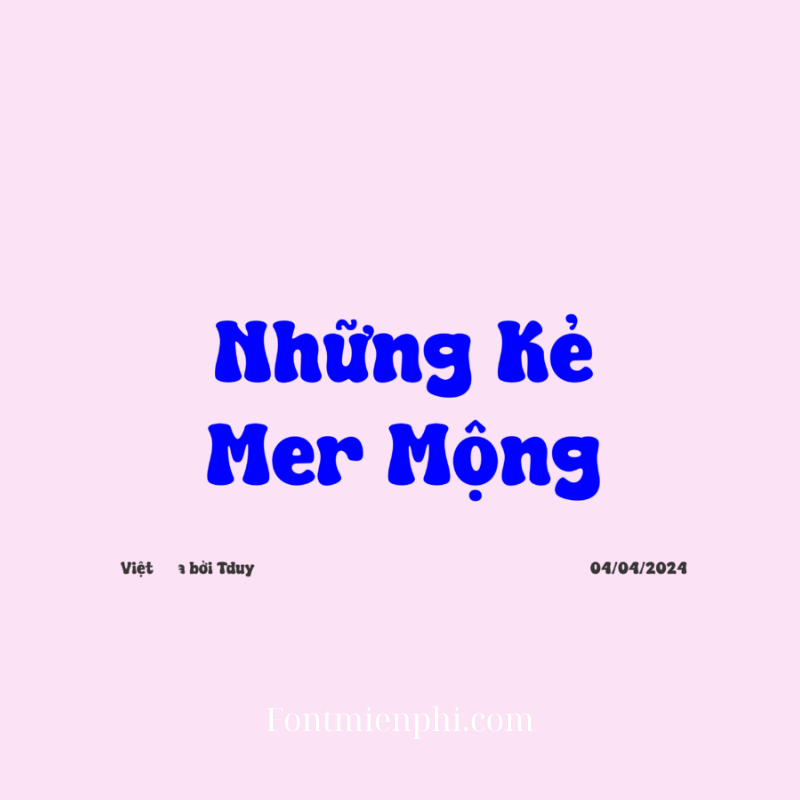
Việt hóa font DL Super Dream
Việt Hóa Font DL Super Dream – Phông Chữ Đẹp, Sáng Tạo Cho Thiết Kế
Giới thiệu
Font DL Super Dream là phông chữ nghệ thuật được ưa chuộng nhờ nét chữ mềm mại, thanh thoát. Tuy nhiên, bản gốc chưa hỗ trợ tiếng Việt, gây khó khăn cho người dùng. Việt hóa font DL Super Dream ra đời khắc phục hạn chế này, mang đến bộ ký tự đầy đủ dấu tiếng Việt, phù hợp cho thiết kế đồ họa, in ấn, hoặc sáng tạo nội dung.
Đặc điểm nổi bật
• Hỗ trợ đầy đủ bảng mã Unicode: Việt hóa font DL Super Dream tương thích với mọi phần mềm thiết kế như Photoshop, Illustrator, CorelDraw.
• Nét chữ độc đáo: Kiểu chữ mỏng, thanh lịch, phù hợp làm logo, poster, banner hoặc thiệp mời.
• Tối ưu cho tiếng Việt: Bổ sung dấu thanh chuẩn, đảm bảo tính thẩm mỹ khi trình bày văn bản.
Ứng dụng
Font DL Super Dream Việt hóa thích hợp cho:
✔ Thiết kế thời trang, mỹ thuật
✔ Làm tạp chí, tài liệu quảng cáo
✔ Trình bày slide, video marketing
Kết luận